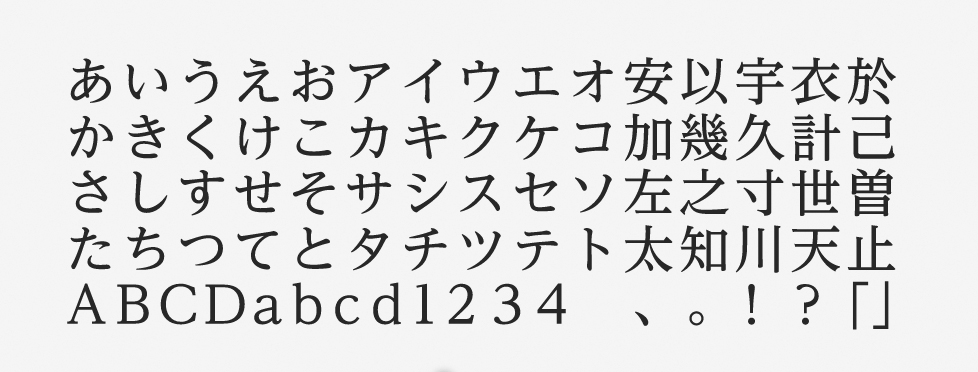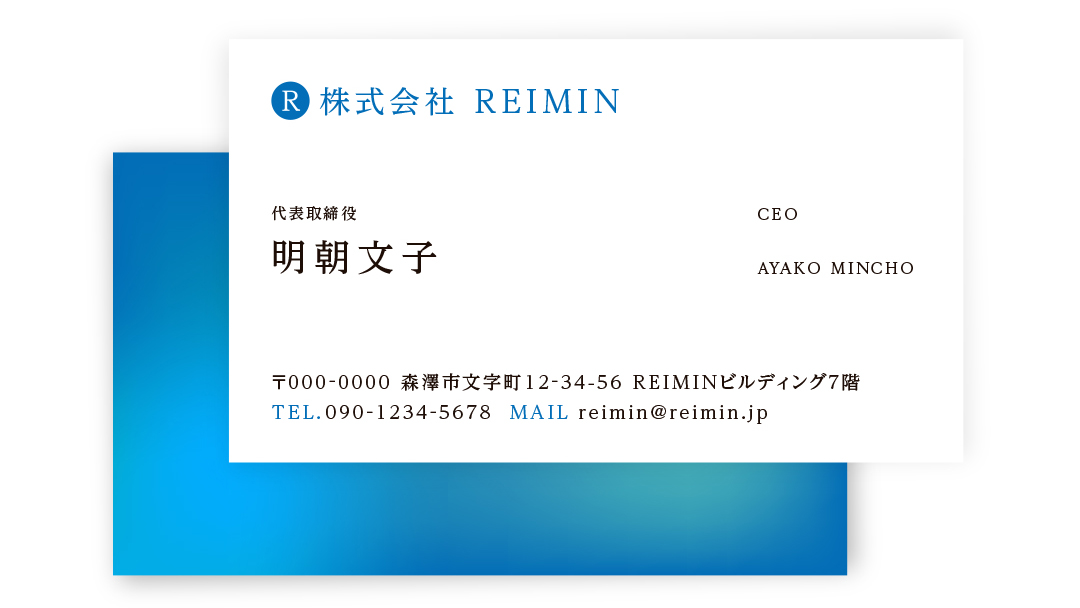
「UD黎ミン」について
「文字のかたちが分かりやすいこと」「文章を読みやすいこと」「読み間違えにくいこと」という3つのコンセプトに沿って開発されたモリサワUD(ユニバーサルデザイン)フォントの1つです。大学や医療機関などの第三者機関との研究で、可視性や可読性の高さが証明されています。現代的な明朝体の黎ミンをベースに開発されたフォントになります。
「UD黎ミン」の特徴
明朝体は本来であれば横画が細いものですが、UD黎ミンはユニバーサルデザインを意識して横画にしっかりとした太さを持たせています。現代的な黎ミンの特徴でもあったかな文字のふところの大きさをはじめ、随所に見やすさ・読みやすさを高める工夫が盛り込まれたフォントです。
英数字でもその特徴は共通しており、シンプルで誤読が起きにくい字形が採用されています。縦組みでも横組みでも使用でき、美しい並びの文字組みを実現することが可能です。
従属欧文・数字も見やすいかたちなので、わざわざ混植しなくてもそのまま使えて便利です。6ウエイトも揃っているため、使い勝手も良いです。作例の名刺のように、1つのフォントでウエイトを変えて全体を構成しやすく、大きな文字から小さな文字まで英数字も含めて統一感を出せます。